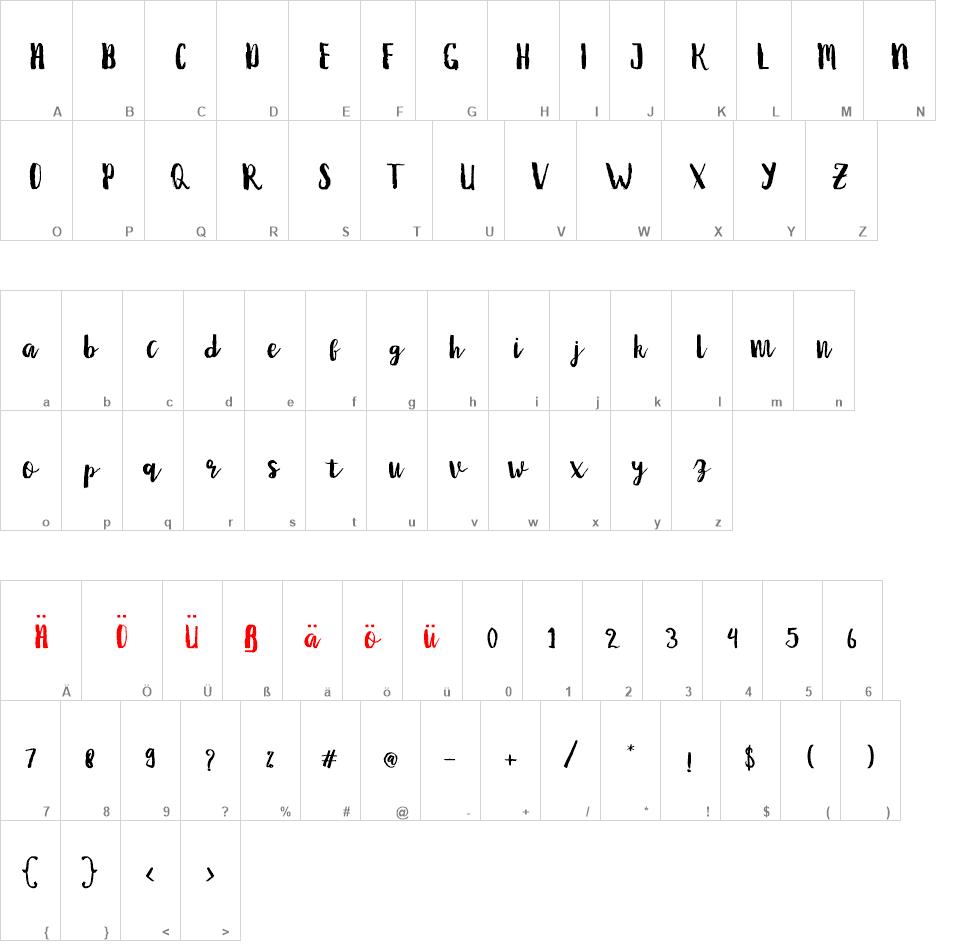
Debt Collectors
Debt Collectors font
Debt Collectors
Schuldeneintreiber
Wiederum präsentiert eine Handbürste Produkte. Der Stil der Handschrift und unregelmäßig, aber immer noch elegant, und Sie werden es genießen, diese Schriftart zu verwenden.